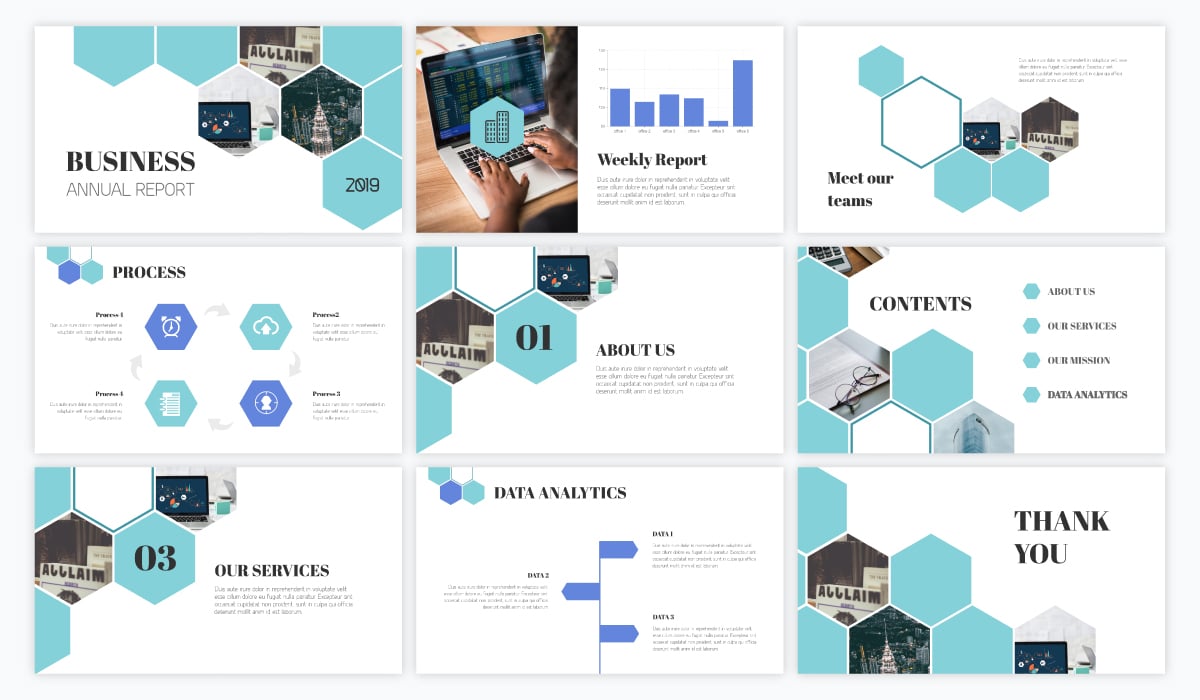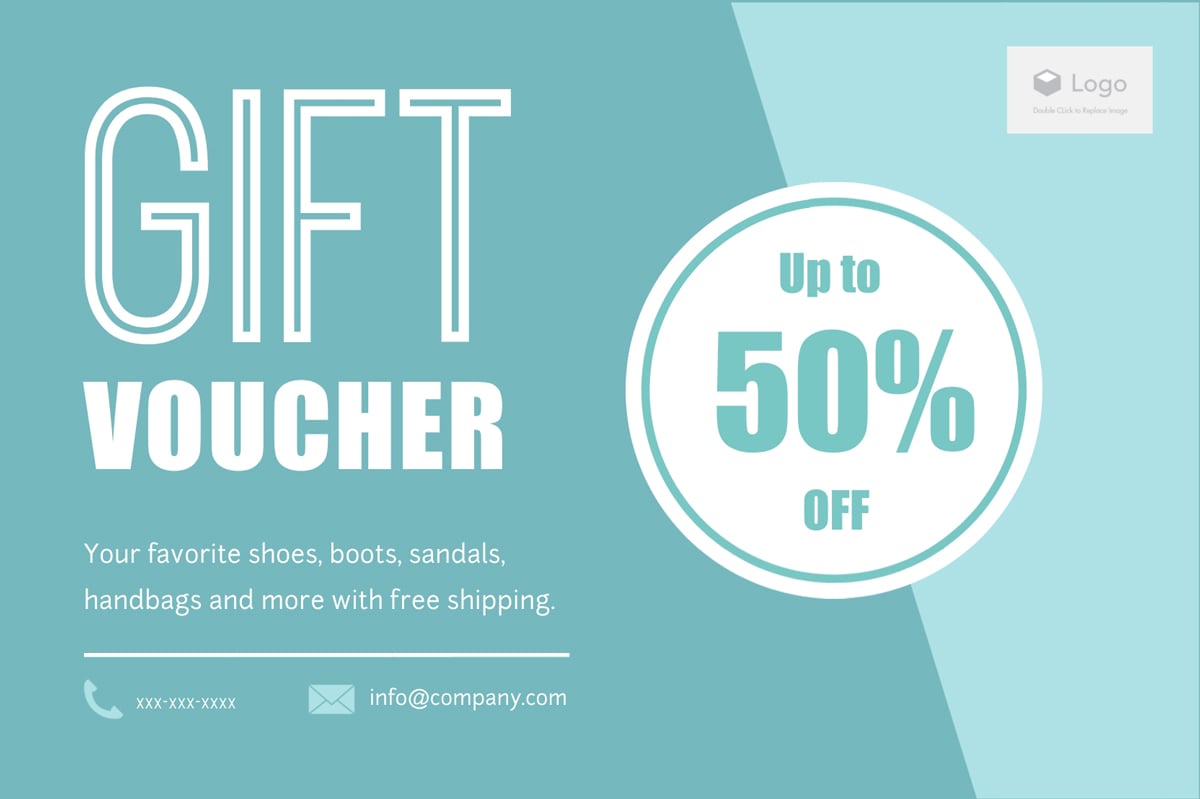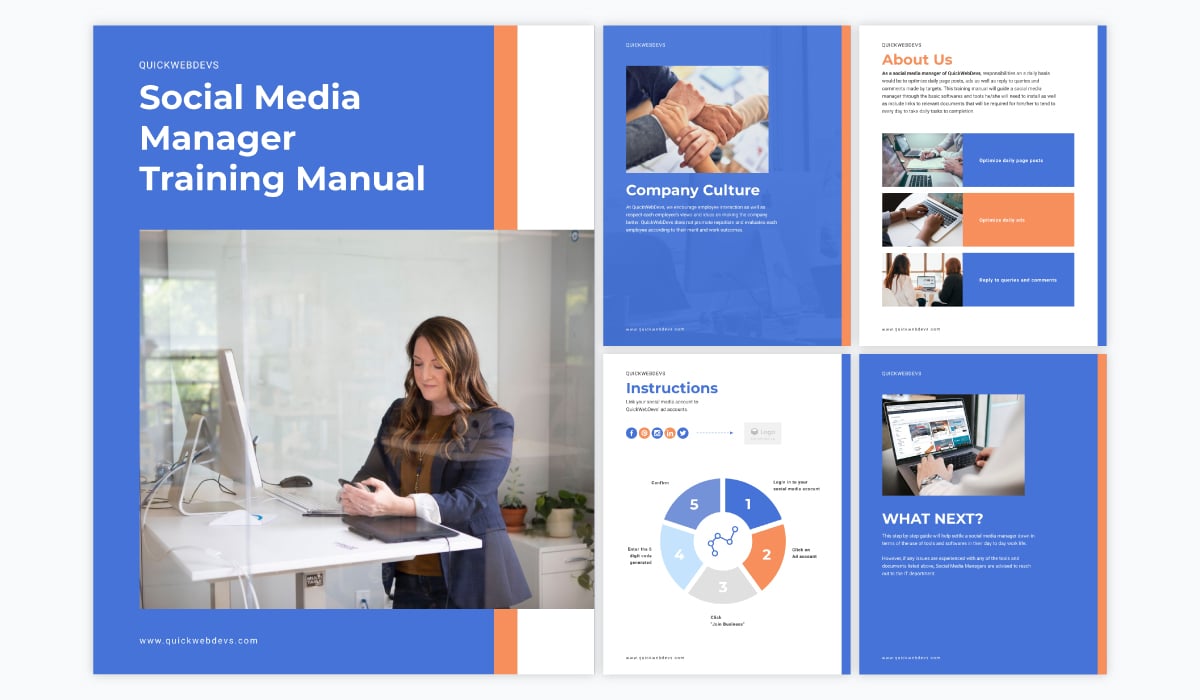
Zu den beliebtesten Schriftarten gehören Serifen, serifenlose Schriften, Slab Serif, Skript und dekorative Schriften.
In diesem Leitfaden werden wir einige der bekanntesten Schriftarten analysieren und erklären, wie Sie sie in Ihren Designs verwenden können.
Hier finden Sie eine kleine Auswahl von 8 beliebten Schriftarten, die Sie mit Ihren Designvorlagen verwenden können, um sie mit Visme zu erstellen, zu bearbeiten, zu teilen und herunterzuladen. Unten finden Sie weitere:
Serifenschriften sind die ältesten und grundlegendsten Schriftarten überhaupt. Diese klassische Schriftart kann auf viele verschiedene Arten verwendet werden und wird wahrscheinlich nie aus der Mode kommen.
Diese Schriftart ist an den "Füßen" am oberen und unteren Ende jedes Buchstabens zu erkennen. Es gibt verschiedene Arten von Serifenschriften, aus denen Sie wählen können.
Eines der klassischsten Beispiele für eine Serifenschrift ist Times New Roman, obwohl es heute viel mehr Optionen gibt, aus denen man bei der Erstellung professioneller, gut gestalteter visueller Inhalte wählen kann.
Diese Kategorie basiert auf den ersten römischen Typen. Sie wurden schätzungsweise vom späten 15. bis zur Mitte des 18. Jahrhunderts verwendet. Die Typen des alten Stils sind auch als Garalde-Typen bekannt.
Sie zeichnen sich durch einen starken Kontrast zwischen dünnen und dicken Strichen aus. Heute zeichnen sich Garamond und Goudy Old Style durch dieselben Merkmale aus.
Diese Schrift wurde von John Baskerville eingeführt, einem bedeutenden englischen Drucker und Typografen aus der Mitte des 18. Jahrhunderts. Dieser Stil ist eine Abwandlung der Typen des alten Stils und des neoklassischen Designs, wobei er einige eigene Merkmale übernimmt.
Übergangsdesigns zeichnen sich vor allem durch eine vertikale Betonung in den Schalen der Kleinbuchstaben aus. Sie haben einen großen Kontrast zwischen unterstrichen und horizontal definierten Köpfen.
Sie entstanden im späten 18. Jahrhundert. Der italienische Schriftgestalter Giambattista Bodoni ist eine der bekanntesten Persönlichkeiten im Zusammenhang mit dieser Art von Schrift.
Diese Schriften haben einen abrupten und dramatischen Kontrast zwischen dünnen und dicken Strichen. Die Strichenden sind oft kugelförmig und bieten ein deutlicheres Design mit klar geformten Buchstaben. Sie haben eine vertikale Achse und sind wie die Baskerville durch eine horizontale Betonung gekennzeichnet und haben Schwänze mit einer auffallend kleinen Öffnung.
Diese Schriften werden heute am häufigsten in hochwertigen Modemagazinen verwendet, da sie elegant, ruhig und kontrolliert sind. Zu den modernen Serifenschriften gehören heute unter anderem ITC Bodoni, ITC Fenice, Adobe New Caledonia und Berthold Walbaum.
Dies ist ein Originalentwurf von Robert Beasley, einem englischen Typografen aus dem 19. Jahrhunderts. Es war die erste patentierte Schriftart überhaupt. Es gibt sie in fünf verschiedenen Strichstärken: leicht, schwer, schwarz, fett und lateinisch. Sie hat einen leichten Strichkontrast und erscheint kurz bis mittellang.
Spätere Entwürfe wurden dahingehend geändert, dass sie schwerere und deutlichere Striche und längere Serifen aufwiesen. Zu dieser Familie gehören Bookman, Nimrod und ITC Charter.
Serifenschriften eignen sich perfekt für klassische, professionelle Anwendungsfälle, wie z. B. Verkaufsgespräche, Posts in sozialen Medien oder Marketingaktionen im B2B-Bereich.
Eine weitere gute Möglichkeit, Serifenschriften zu verwenden, ist in einem professionellen B2B-Dokument wie einem Angebot. Schauen Sie sich an, wie wir eine fette Serifenschrift in die Überschriften dieser Angebotsvorlage integriert haben.
Sie können Serifenschriften auch mit vielen anderen Schriftarten kombinieren, einschließlich serifenlosen Schriften und Schriftarten, die wir in Kürze behandeln werden.
Diese Klassifizierung geht auf das französische Wort "sans" zurück, das wörtlich "ohne" bedeutet. "Serif" hingegen stammt vom niederländischen Wort "schreef", was "Linie" bedeutet. Diese besondere Schriftfamilie weist im Vergleich zur Serifenschriftfamilie eine geringere Variation der Strichstärke auf.
Wie der Name schon sagt, brachen diese Schriften mit der historischen Eleganz von Serifenschriften. Grotesk-Schriften wurden stark von der modernen Serifenschrift (Didone) beeinflusst.
Außerdem sind sie prall und fest. Sie wurden hauptsächlich für Schlagzeilen und Werbung vom späten 19. bis zum frühen 20.
Sie zeichnen sich durch eine vertikale Achse, eine begrenzte Variation der Strichstärke und horizontal akzentuierte Kurven aus. Diese Schriftarten sind beliebt, weil sie einfach und praktisch sind.